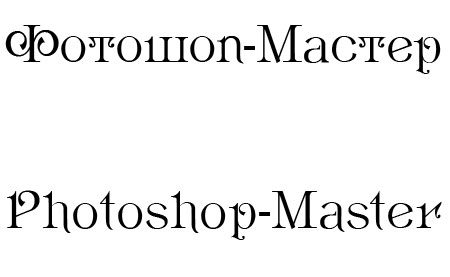
Красивый
Очень класный шрифт!!!!
очень красивый шрифт)
классный шрифт))
Этот шрифт неплохо подошёл бы к уроку Сумерки)
симпотичный^^
Прикольный шрифт)